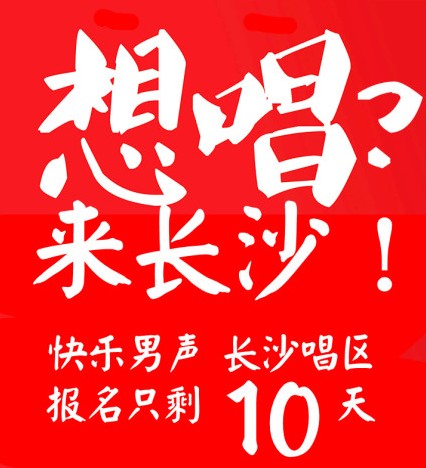
軟件介紹 軟件標簽: 文鼎字體 字體 文鼎大顏楷簡體是一款很受歡迎的字體,因為這是2013快樂男聲宣傳片使用的字體,這款字體是真實可用的,下載后不會出現不是有效字體文件提示,所以大家放心下載使用吧!文鼎大顏楷字體使用方法將字體文件復制到C:\Windows\Fonts文件夾即可完成安裝(Win7用戶可直接右鍵選擇“安裝”菜單進行安裝)。 綠色資源網所有字體資源僅供個人學習與參考,如需商業使用請到相關官網授權。 軟件截圖 上一張下一張(1 / 1) 安裝詳細截圖 猜你喜歡 免費字體 顏體字體 免費字體 免費字體有哪些?免費字體下載專區包含了宋體、楷體、隸書、仿宋、黑體、幼圓等等各種好看的免費字體,各種字體都各具特色,適用領域也非常的廣泛,深受廣大朋友們的喜愛,需要的朋友歡迎來綠色資源網下載! 查看更多>> by jossq dmf in beijing字體 1.46M/中文/0.9/下載 gska00h 1.32M/中文/10.0/下載 gbjenlei medium 22.12M/中文/0.0/下載 yankaigungeg ultra gb 3.80M/中文/3.2/下載 漢儀顏楷簡字體 3.71M/中文/1.6/下載 漢儀鑄字美心體 1.16M/中文/2.5/下載 顏體字體 顏體是一款極具古樸厚重韻味的字體,這里匯集了各具特色的顏體字體,每款字體都有著顏體豐腴雄渾、骨力遒勁的魅力,因此顏體也深受廣大書法家的喜愛,下面有綠色資源網小編為大家提供顏體字體下載大全,感興趣的朋友歡迎來綠色資源網下載體驗! 查看更多>> 經典簡顏體字體 2.44M/中文/1.2/下載 tianshi-yanti字體 2.92M/中文/5.0/下載 全真顏體簡體字體 4.88M/中文/2.5/下載 fashionfont052 by字體 2.44M/中文/2.0/下載 刻石錄顏體字體 8.53M/中文/5.7/下載 其他版本下載 標題 大小 更新日期 下載 文鼎cs大宋 2.35M 2019-05-29 下載 文鼎cs隸書字體 免費版 3.36M 2017-01-10 下載 文鼎cs楷體 ttf免費版 2.76M 2017-01-10 下載 文鼎cs中黑 ttf免費版 2.06M 2017-01-11 下載 文鼎霹靂簡體字體 4.47M 2017-05-20 下載 文鼎中隸繁 2.91M 2019-06-04 下載 62款文鼎字體打包 223.94M 2019-06-06 下載 文鼎粗明體 5.26M 2017-02-23 下載 文鼎大鋼筆行楷 123KB 2019-06-06 下載 文鼎霹靂字體 mac版 7.73M 2017-05-20 下載 下載地址 電腦版 文鼎大顏楷簡體 點擊報錯 軟件無法下載或下載后無法使用,請點擊報錯,謝謝! 關閉報錯反饋 請描述您所遇到的錯誤,我們將盡快予以修正,謝謝! *必填項,請輸入內容 本類最新 文鼎霹靂繁體字體 文鼎妞妞字體 文鼎cs魏碑簡 文鼎cs粗圓繁ttf 文鼎cs大黑繁體 文鼎cs舒同體繁字體 相關文章 Photoshop字體安裝使用方法和技巧 如何解決“無法新增字體”問題 Win 7系統安裝字體方法 網頁字體大小設置方法 怎么改網頁字體大小 在Linux系統中安裝字體的幾種方法 windows7字體顯示問題:打開某些程序的時候顯示的是亂碼 用戶評論 熱門評論 最新評論 第 1 樓 四川綿陽鹽亭縣客人 發表于: 2017/05/11 22:24:27 文鼎大顏楷字體給人感覺既端莊又厚重,還有飄逸感,非常有個性的字體啊! 支持(16) 蓋樓(回復) 發表評論 查看所有評論(1) 昵稱: 請不要評論無意義或臟話,我們所有評論會有人工審核. 字數: 0/500 (您的評論需要經過審核才能顯示)